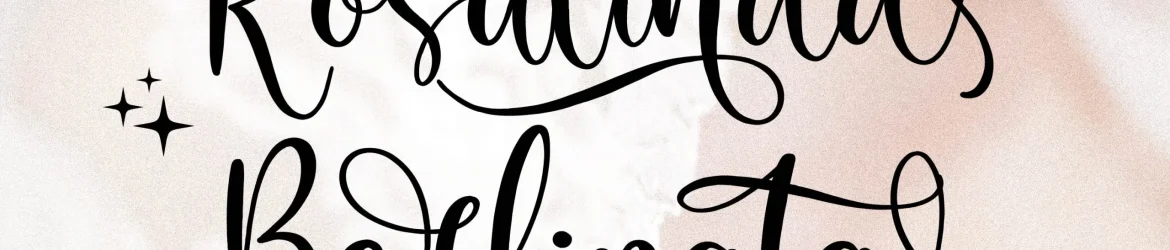
Rosalinda Berlinata Font – Download Grátis
A Rosalinda Berlinata é uma linda fonte de calligrafia romântica que se destaca para projetos diversos, desde criação de logomarcas e designs de marca até embalagens de produtos e design gráfico geral. Sujeitável a diversas aplicações como identidade visual de empresas, rótulos de produtos, cartões de visita, cartazes, selos, capas de livros, adesivos para móveis, entre muitos outros usos em que você precisa de um toque romântico e sofisticado. Esta fonte é perfeitamente adaptada a qualquer projeto em que uma pitada de elegância e delicadeza seja necessária, seja ele um design personalizado para um novo produto ou a recriação de sua própria identidade visual. A Rosalinda Berlinata oferece a você uma gama de opções únicas para tornar seus projetos ainda mais amados e memoráveis.